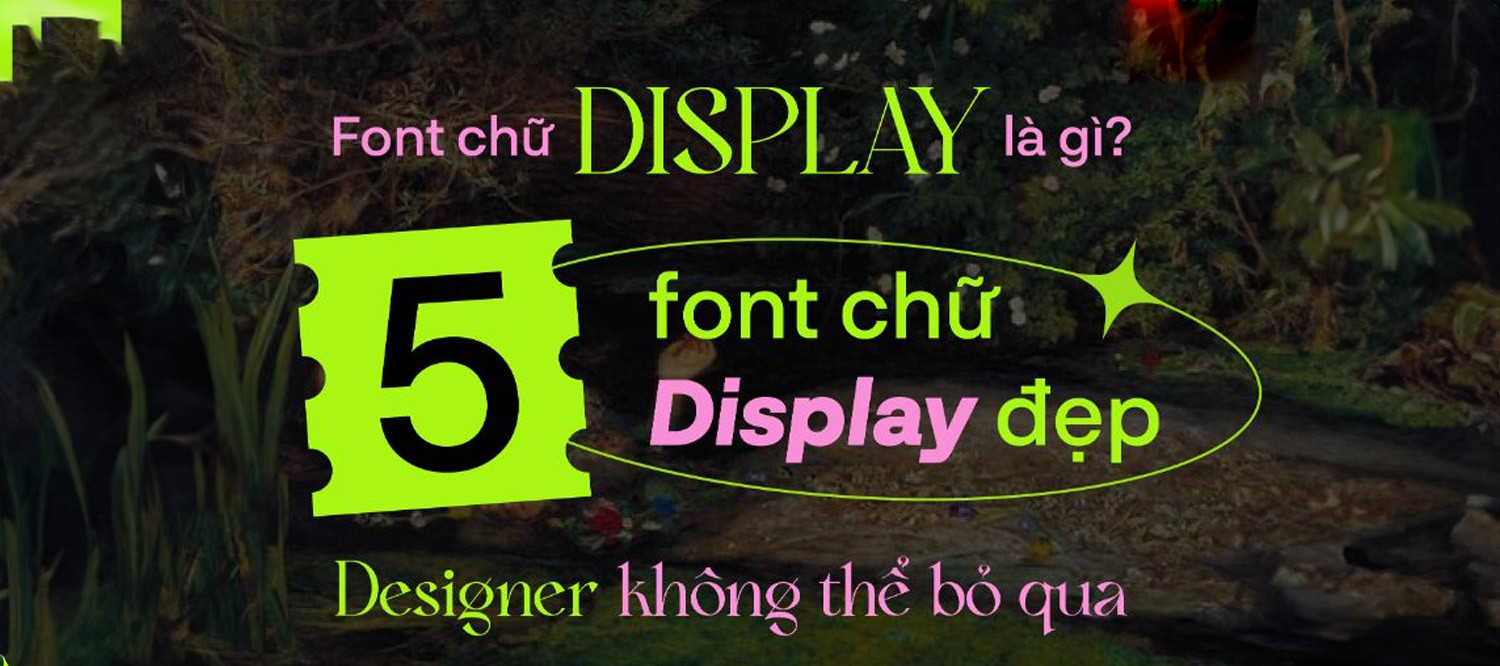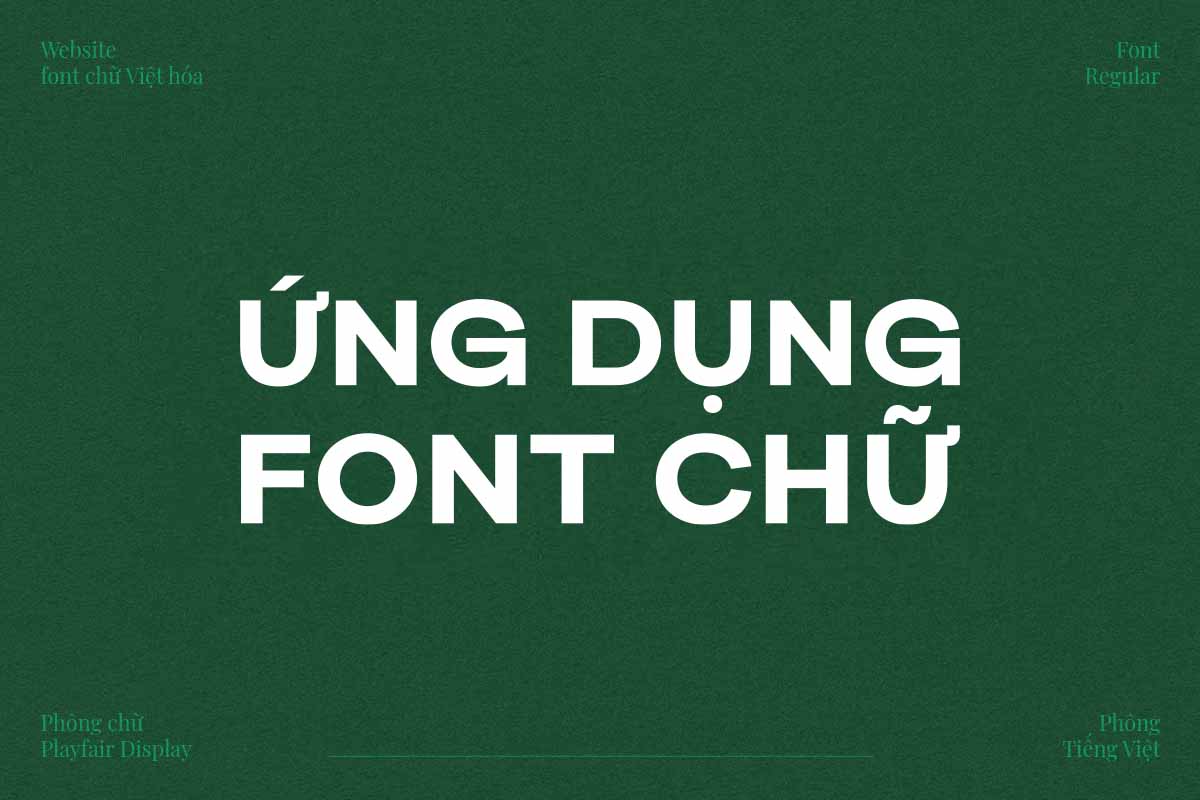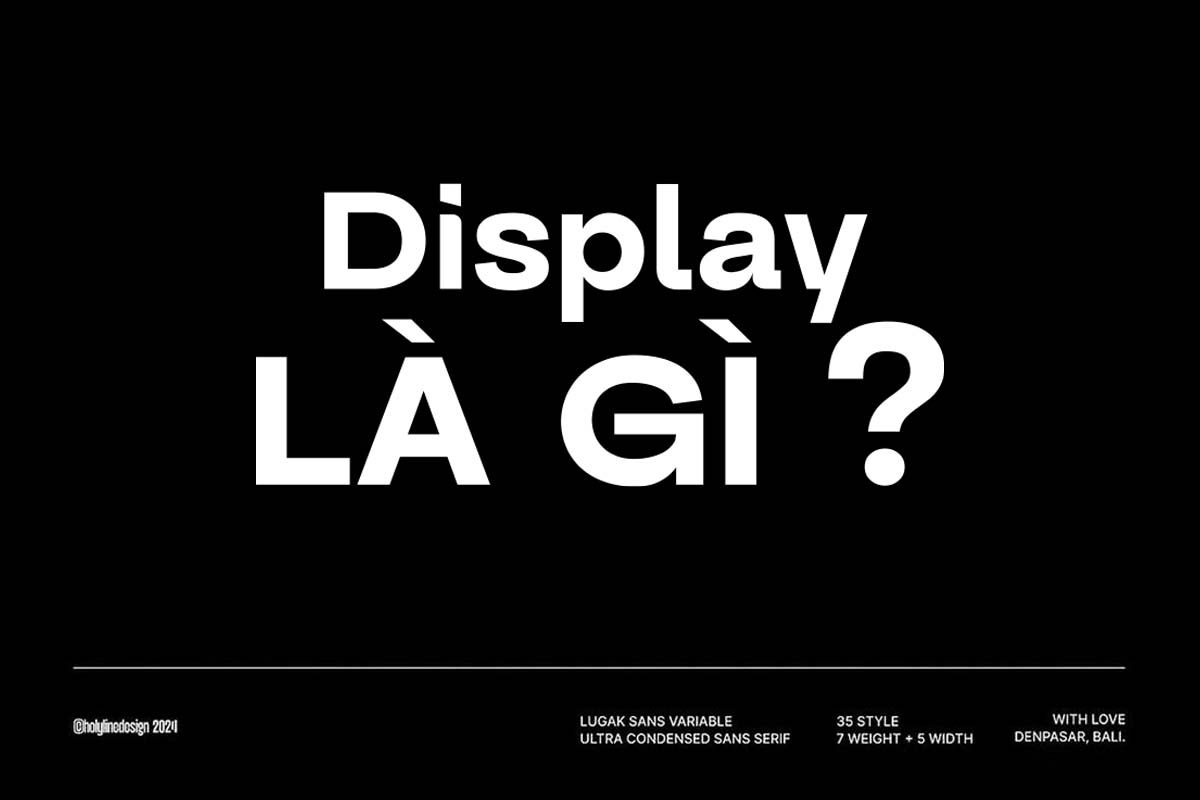
Danh Sách 15+ Font Chữ Display Tiếng Việt Miễn Phí và Trả Phí
Font chữ display là một trong những lựa chọn được designer ưa chuộng nhất khi muốn tạo sự ấn tượng trong thiết kế. Trong bài viết này, S99.vn sẽ giới thiệu đến bạn danh sách 15+ font chữ display đã Việt hóa đẹp nhất hiện nay – bao gồm font miễn phí và trả phí – phù hợp cho nhiều lĩnh vực thiết kế từ logo, bao bì đến poster hay thiệp cưới.
Font chữ display là gì?
Font display là nhóm font được thiết kế dùng cho tiêu đề, bên ngoài trang, hay những đoạn văn ngắn cần tạo sự chú ý. Khác với font body text đơn giản dễ đọc, font display thường mang cá tính mạnh, phá cách, trang trí và rất linh hoạt trong phong cách.
Từ poster sự kiện, banner quảng cáo cho tới bìa tạp chí, thiết kế sản phẩm cao cấp – font display giúp tên thương hiệu hoặc thông điệp trở nên đậm nét và dễ nhớ.
Ứng dụng thực tế của font display trong thiết kế
Font chữ display giữ vai trò nổi bật trong thiết kế nhờ khả năng tạo điểm nhấn thị giác và truyền tải cảm xúc rõ rệt. Với kiểu dáng to bản, sáng tạo hoặc trang trí độc đáo, nhóm font này thường được sử dụng cho tiêu đề, poster, banner quảng cáo – những nơi cần gây ấn tượng ngay tức thì. Trong các lĩnh vực như thiệp cưới, thời trang, mỹ phẩm, font display giúp thể hiện phong cách thiết kế – từ lãng mạn, cổ điển đến hiện đại, mạnh mẽ.
Bên cạnh đó, nhiều font display mang hơi hướng văn hóa như thư pháp Nhật Bản, Hàn Quốc, hay phong cách retro, cổ trang cũng rất phù hợp cho dự án truyền thống hoặc quảng bá di sản. Trên nền tảng số như Instagram, YouTube hay TikTok, font display giúp nội dung nổi bật hơn, tăng khả năng thu hút và chia sẻ. Nhờ tính tạo hình đa dạng, font display không chỉ đóng vai trò thẩm mỹ mà còn góp phần định hình cá tính và thông điệp trong thiết kế chuyên nghiệp.
Cách chọn font display phù hợp
Khi chọn font chữ display, điều quan trọng là xác định rõ mục đích thiết kế. Với lĩnh vực cưới hỏi, thời trang hay mỹ phẩm, nên chọn các font mềm mại, bay bổng; trong khi đó, lĩnh vực thể thao hay công nghệ phù hợp hơn với font mạnh mẽ, hiện đại. Ngoài cảm xúc, hãy cân nhắc ngữ cảnh sử dụng: banner, poster, tiêu đề sẽ cần font đậm, dễ đọc từ xa. Đặc biệt, nếu thiết kế cho thị trường Việt Nam, hãy ưu tiên các font đã Việt hóa đầy đủ để đảm bảo tính thẩm mỹ, dễ đọc và không gây lỗi hiển thị khi in ấn hay xuất bản.
FONT CHỮ DISPLAY TRẢ PHÍ
1. Font display thanh lịch, sang trọng
TH Luxury 8: Kiểu sans-serif mang đường nét hình học tinh gọn, hiện đại và cân đối. Font được phát triển bởi đội ngũ thiết kế quốc tế, phù hợp với thương hiệu cao cấp.
TH Luxury 2: Dòng serif thanh mảnh, đậm chất châu Âu cổ điển. Các nét chữ có độ tương phản cao, tạo vẻ sang trọng và tinh tế.
TH Luxury 4: Mang phong cách cổ điển, thanh lịch với các đường nét uốn lượn tinh xảo, serif mềm mại, tạo cảm giác sang trọng, phù hợp cho thiết kế thiệp cưới hoặc tiêu đề nghệ thuật.
TH Griffiths: Font serif mang phong cách quý phái, cân xứng cao, lý tưởng cho thiệp cưới và thiết kế in ấn cao cấp.
2. Font display viết tay, cổ trang, mang phong cách nghệ thuật
TH Pinland: Font viết tay với nét tròn, đều, mang lại cảm giác tự nhiên và gần gũi. Lấy cảm hứng từ chữ viết tay truyền thống phương Tây.
TH Honya: Mô phỏng phong cách thư pháp Nhật Bản, font có đường nét mạnh mẽ và cân bằng, phù hợp với thiết kế văn hóa – lịch sử.
TH Hulahoy: Font script với nét uốn lượn, mảnh mai, truyền cảm hứng lãng mạn, nữ tính. Thích hợp với thương hiệu làm đẹp hoặc thời trang.
FONT DISPLAY MIỄN PHÍ
3. Font vintage, retro, cổ điển
TH Vintage 1: Mang hơi thở retro, các nét chữ cong nhẹ và dày bản gợi nhớ phong cách typography thập niên 60–70.
MTD Barakah: Lấy cảm hứng từ thư pháp cổ trang, font sử dụng nét vẽ thô và cọ bản lớn để tạo sự cổ kính và quyền uy.
4. Font viết tay mềm miễn phí
Indulge Script: Font viết tay mềm mại, có độ nghiêng tự nhiên, đường cong mượt mà, tạo cảm giác thư giãn và tinh tế.
SVN Buinton: Phong cách bán cổ điển, với nét chữ uốn lượn mềm mại. Font này đặc biệt phù hợp cho thiết kế thiệp hoặc tiêu đề blog nghệ thuật.
5. Font hiện đại, mạnh mẽ, brush
SVN Mission X: Font đậm, góc cạnh, có phong cách sci-fi và thể thao điện tử, dùng tốt cho tiêu đề video hoặc game.
SVN Redtowns: Nét cọ mạnh và ngẫu hứng, mô phỏng brush thủ công. Font được thiết kế với cảm hứng graffiti và nghệ thuật đường phố.
SVN Korean Calligraphy: Lấy cảm hứng từ thư pháp Hàn Quốc, nét cọ bản rộng, uốn cong táo bạo, rất phù hợp với thiết kế châu Á hiện đại.
FAQ - Câu hỏi thường gặp
Font display là gì?
Đây là font dùng cho tiêu đề, được thiết kế nhằm tạo sự độc đáo thị giác.
Font display có dùng cho đoạn văn dài được không?
Thường không nên, vì dễ gây mệt mắt khi đọc nhiều.
Nên nhóm font display theo kiểu nào?
Theo phong cách (retro, viết tay, sans-serif), theo ứng dụng (cưới, quảng cáo).
Font serif hay script hợp cho thiệp hơn?
Font script viết tay mềm mại thường được chuộng hơn.
Kết luận
Bộ font chữ display được Việt hóa không chỉ giúp tiết kiệm thời gian cho nhà thiết kế mà còn nâng tầm cảm xúc và độ chuyên nghiệp cho sản phẩm. Hãy lựa chọn font phù hợp để thiết kế của bạn không chỉ đẹp mà còn truyền tải đúng thông điệp.